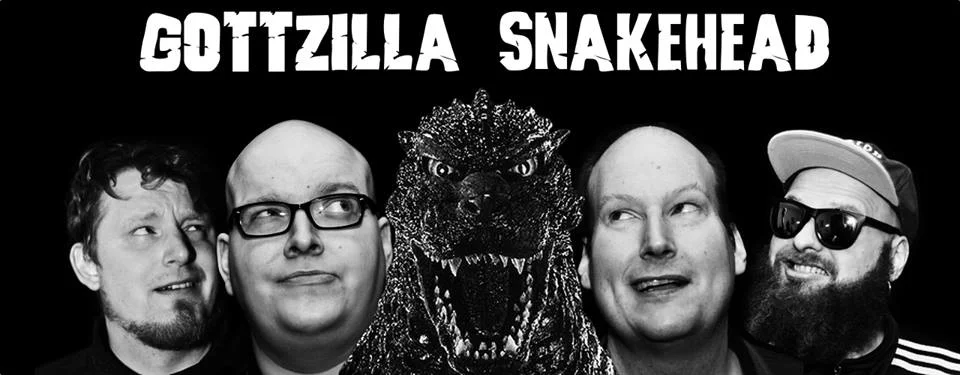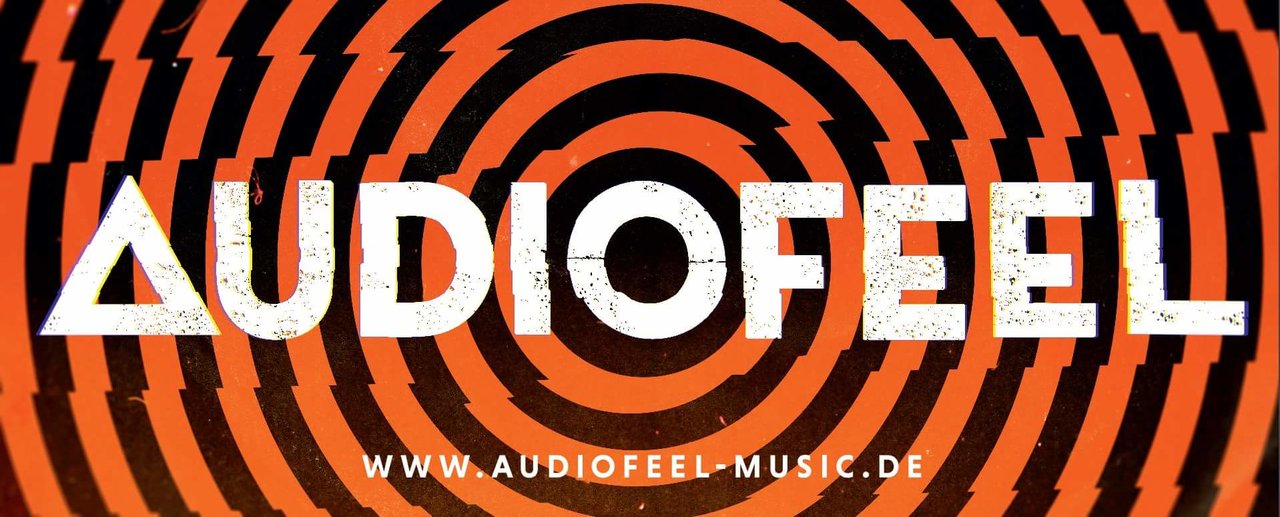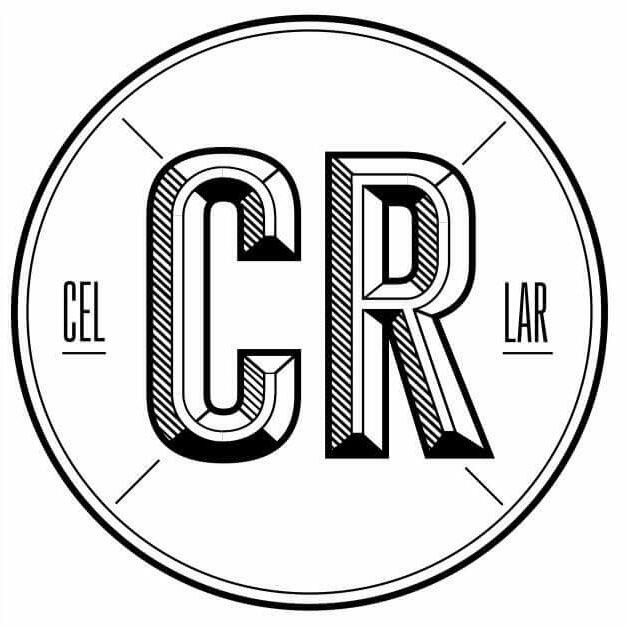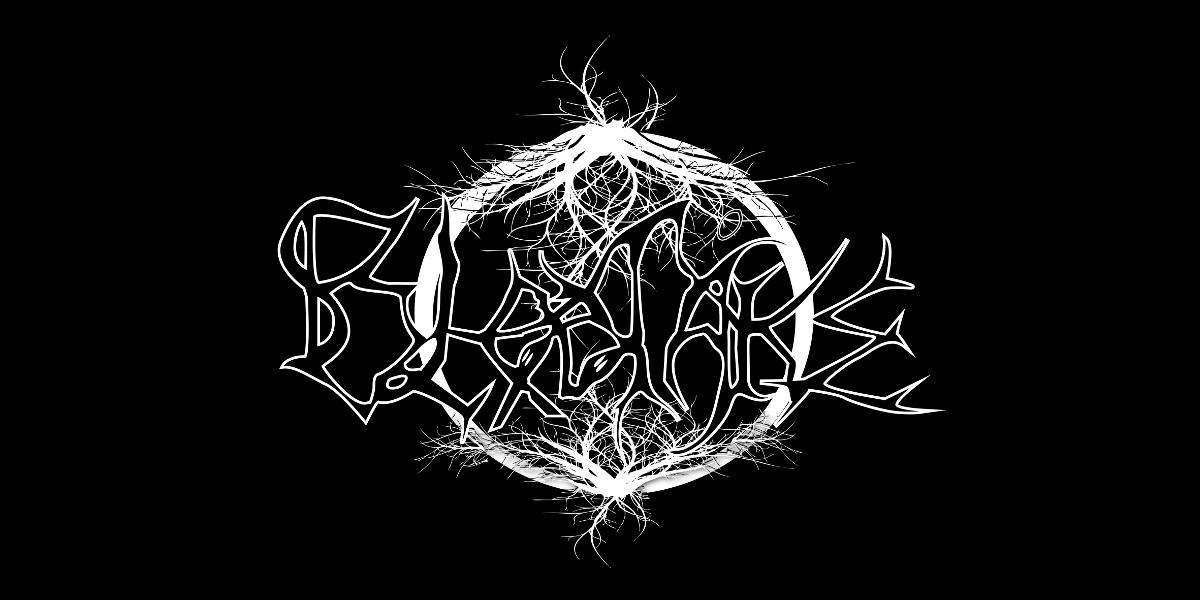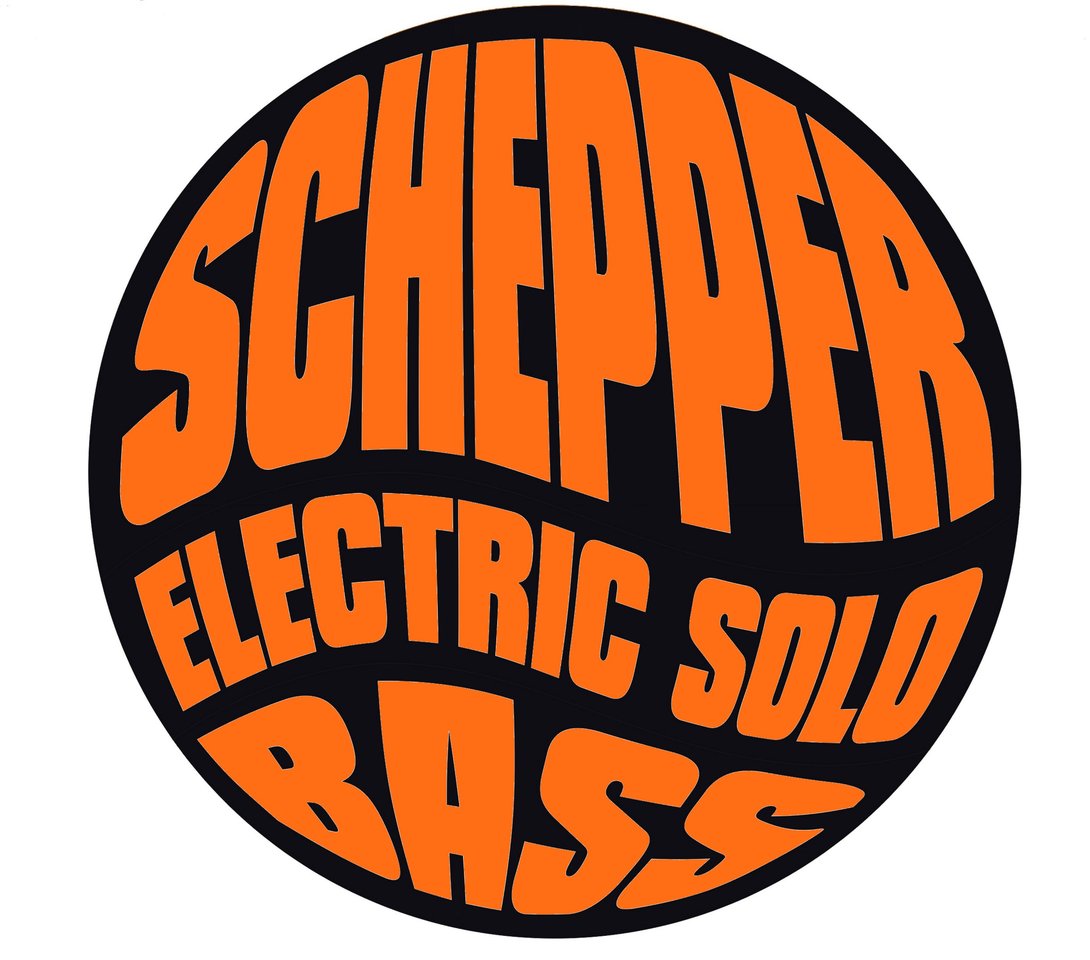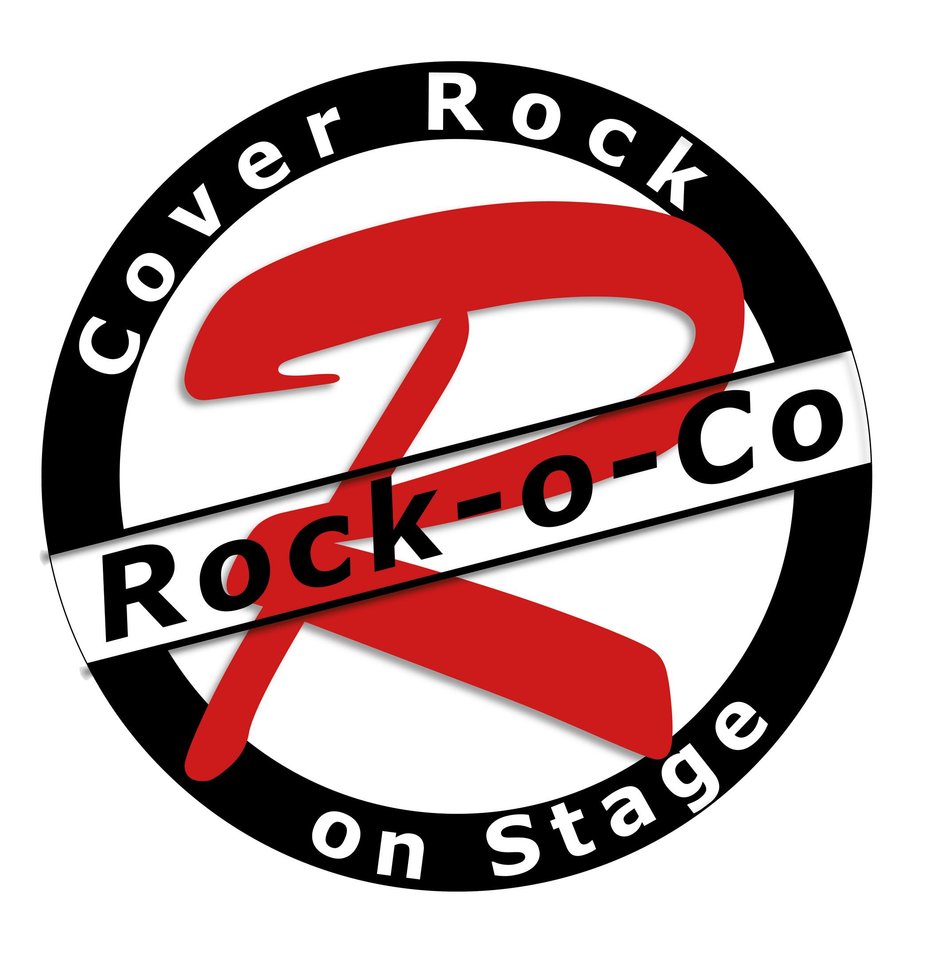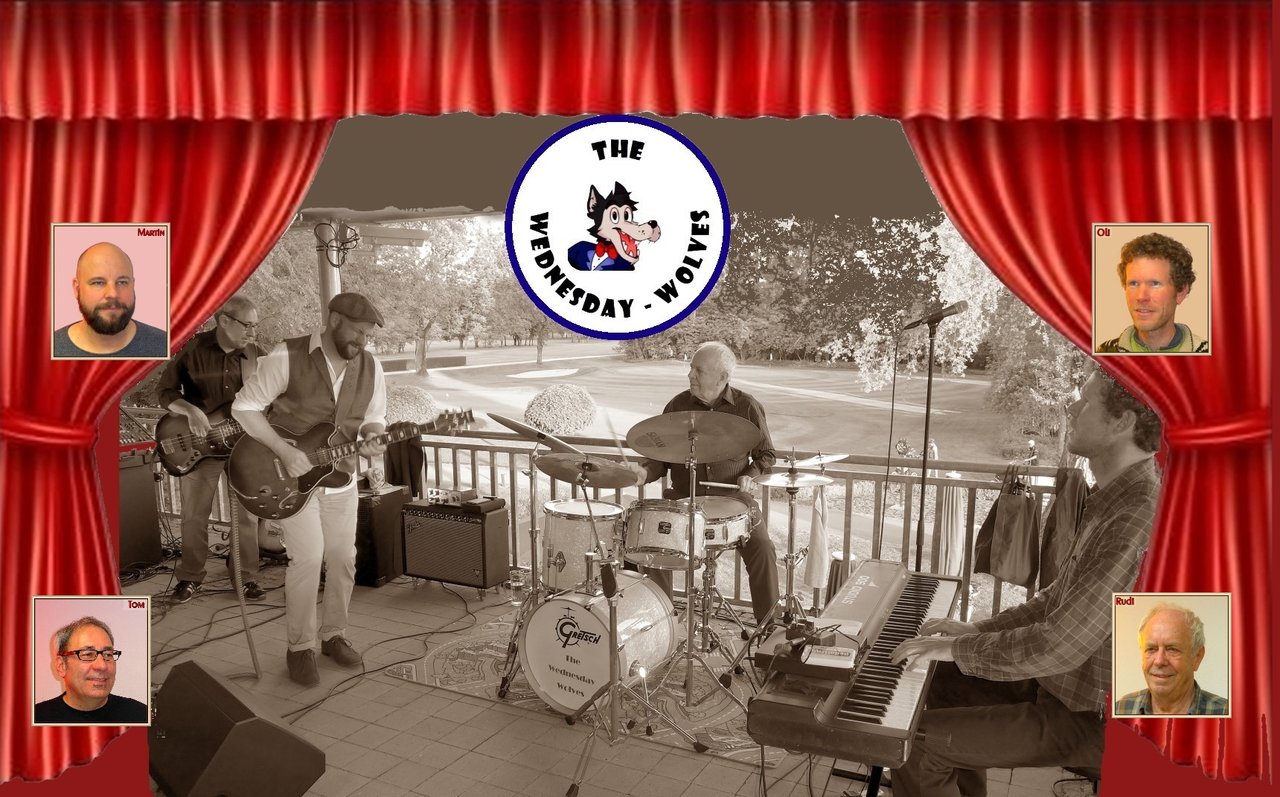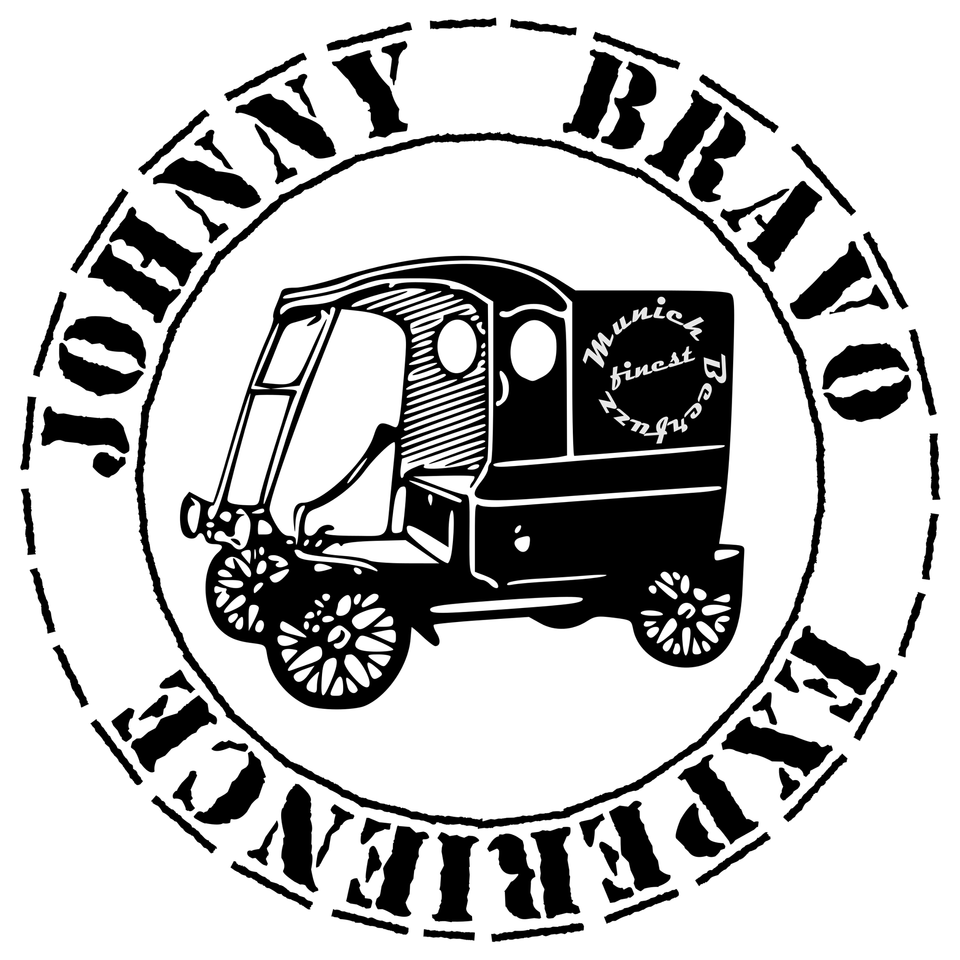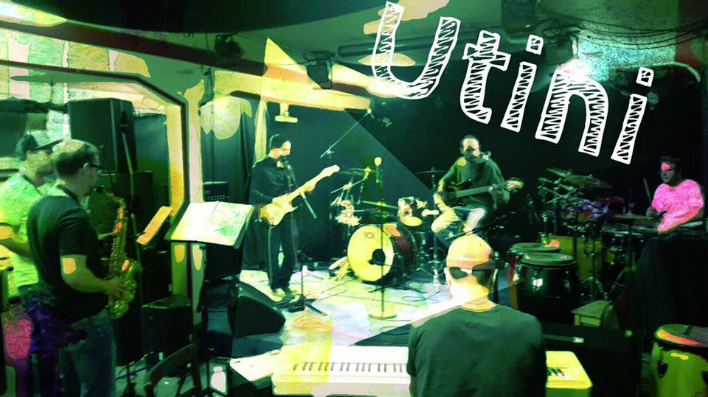
Euer Bandlogo-Artwork-Schriftart... her damit...!
Oft ein mühsamer, manchmal kontroverser aber immer interessanter Prozess...
Die Namensfindung, das grafische Layout, die Schriftart, ein Logo (wenn gewünscht) ...
und alle reden mit, jedem soll es gefallen, es soll die Musik und das Selbstverständnis der Band optimal ausdrücken und am Ende dann auch die gemeinsame Identifikation stärken... kennt wohl jeder.
Wer Lust hat, kann hier mal kurz schildern, wie es zu dem Bandnamen gekommen ist, wie lange es gedauert hat, was vielleicht lustig, interessant oder schwierig dabei war und sollte dann natürlich das Ergebnis hier kurz uploaden: also Eurer Schriftzug/Font, Logo und eine kurze Geschichte dazu.
Tja, scheinbar spielen Bandnamen oder Logos nicht so eine große Rolle im Forum - wenn man das bisherige Feedback betrachtet ... oder Bassisten machen sich darüber keine Gedanken bzw. sind in die kreative Phase nicht involviert ;-)...
Also, der Name unserer Chicago-Blues-Combo "The Wednesday Wolves" hat sich a) aus unserem Probetag ergeben und b) soll zugleich eine Huldigung an Howlin Wolf sein ... im Gespräch war noch irgendwas mit "Kings", weil wir hauptsächlich Songs von Freddie und Albert spielen - aber das mit den Königen klingt irgendwie zu hochtrabend ...
Das Logo stammt von der Nichte unseres Gitarristen, die einfach gerne zeichnet ... es ist auch noch geplant, einen Wolf als Keyboarder, Schlagzeuger und :m_dblbass: zu entwerfen ... die Website wird auch noch weiter überarbeitet ...
Unser Bandname Johnny Bravo Experience hat sich aus einem Gehirnfurz von mir ergeben, den ich so in den Raum geschmissen hab. Hat allen gefallen, fertig.
Das Logo ist erst in den letzten Monaten so langsam entstanden und auch noch in Entwicklung. Abgesehen davon ist dieses Logo aber nicht in Stein gemeißelt. Wenn einer aus der Band mit was besserem kommt, kann es sich auch wieder ändern.
Hmmm .. der Bandname bestand schon da es mal ein Projekt unseres Klampfers und Trommlers sein sollte.
Es wurden dann Leute gesucht welche das Ganze mit auf die Beine stellen.
Thematik war zu Beginn typisch Blackmetal hat sich während des Arbeitens an den Songs zu einem Mix aus Blackmetal und Deathmetal entwickelt.
Unsere Gitarristin ist "Grafikerin" und zack war das Logo / der Schriftzug entstanden.
Die Originaldatei ist nicht so pixelig da in 3x2m (Backdrop Druckdatei)
Einmal das hier:
Der Name „Cellar“ entstand da die Mitglieder in ihrer ganzen Laufbahn immer im Keller geprobt haben. Das Logo haben wir von einem uns bekannten Kunststudenten machen lassen, der sollte sich einfach mal austoben. Finde das Logo sehr gelungen! Leider gibt es die Band mittlerweile nicht mehr....
Mein momentanes Hauptprojekt:
Da habe ich beim Bandnamen außer meiner Stimme nicht viel dazugegeben. Das Logo haben wir uns von einem Künstler machen lassen und beinhaltet Logos für Banner, Flyer etc.
Hat ne gute Stange Geld gekostet.
Hier noch der Entwurf für Aufkleber:
Unser Logo geht auf den von uns hochverehrten Stevie Ray Vaughan und einen seiner Songs zurück. Da wir allgemein souligen Bluesrock spielen, passt das ganz gut, wie wir finden. Und natürlich war die Suche nach Namen und Logo eher schwierig aber phasenweise auch ganz lustig. Letztlich haben wir über die letzten Vorschläge geheim abgestimmt und einen Freund als Wahlamt missbraucht. Der Name bekam die meisten Stimmen... Demokratie tut halt auch mal ein bisschen wehB)
Bei Band 1 "Utini" ist unser inoffizielles Logo dieses hier:
Der Name ist aus Witz entstanden... wir sind alles Starwars Fans und brachten immer mal wieder paar Gags von den Filmen etc. rüber... hatten aber lange keinen Namen. Bis zu dem tag als der Veranstalter Flyer drucken wollte, da haben wir uns dann für Utini geeinigt. Das Mit dem Logo ist aber so eine Sache... wir haben etwas bammel davor von Disney gekauftes Material zu verwenden... vermutlich werden wir demnächst mal etwas eigenes basteln... ein Java sollte es aber schon sein;-)
[...] "Utini" [...] "Salida del Sol" [...]
Probenraumfoto ist schön schräg! :great: Die Psychoblumensonne ist schön schön! :great:
[...] ehemalige Schweinerockband [...]
[...] Ziel war ein Logo, was man von weitem erkennt, und nicht so überladen ist. [...] Unspektakulär aber gut.[...]
[...] Name und Schriftzug schon so verwendet wurde, bevor ich in die Band kam :D[...][/ATTACH]
Ok. Aber - was steht da? :igitt: